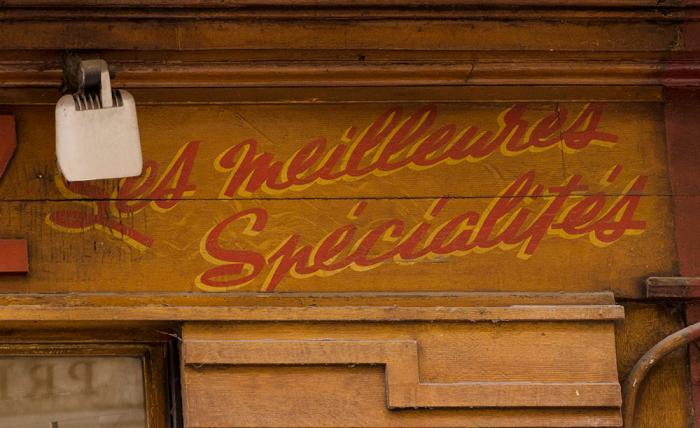
Signpainter Werkzeug
mit was für einem Werkzeug wurde das hier geschrieben?
Ich kenne nur die weichen An- und Abstriche, was war das für ein Werkzeug?
Wird wohl eher ein Breitpinsel gewesen sein. Die funktionieren wie eine normale Bandzugfeder.